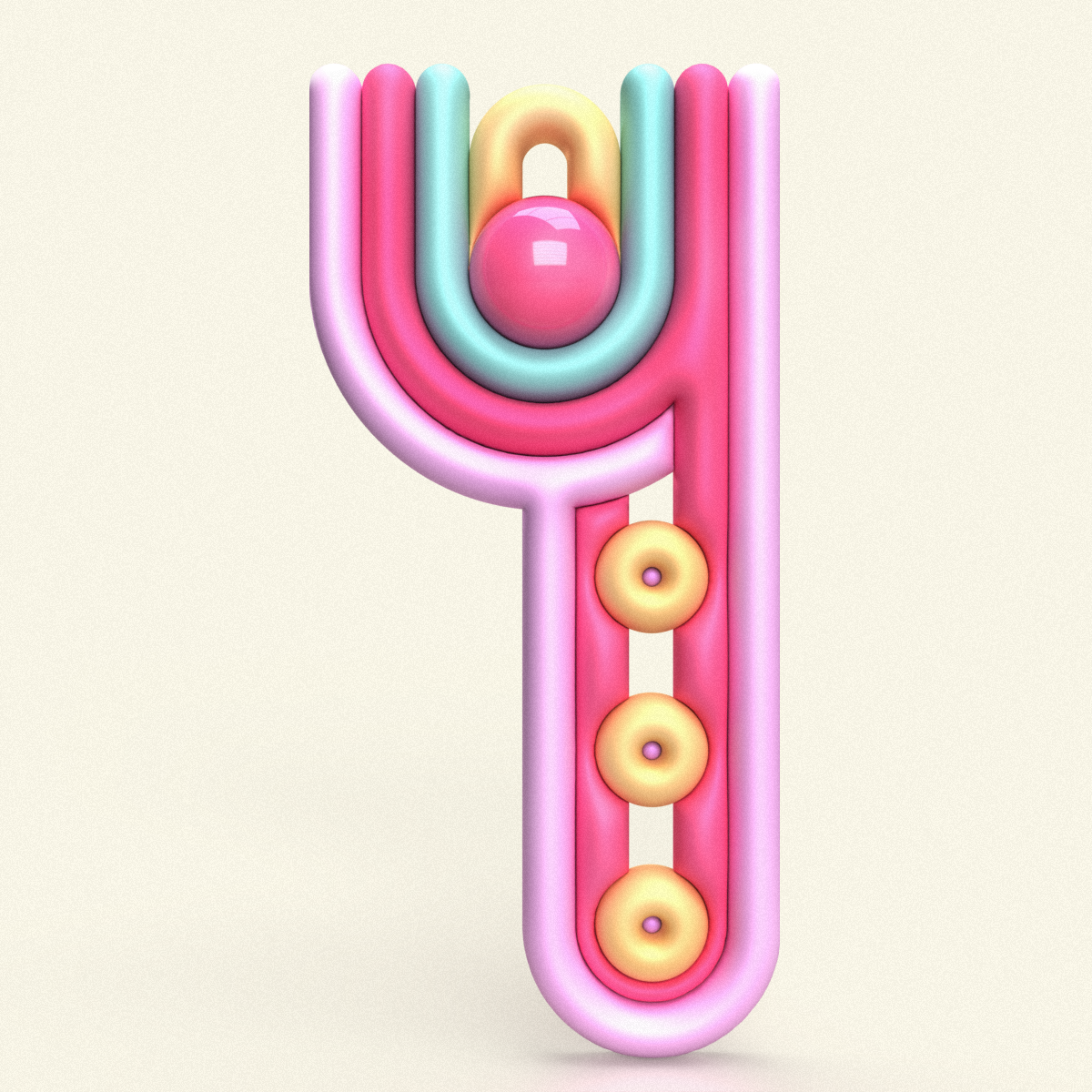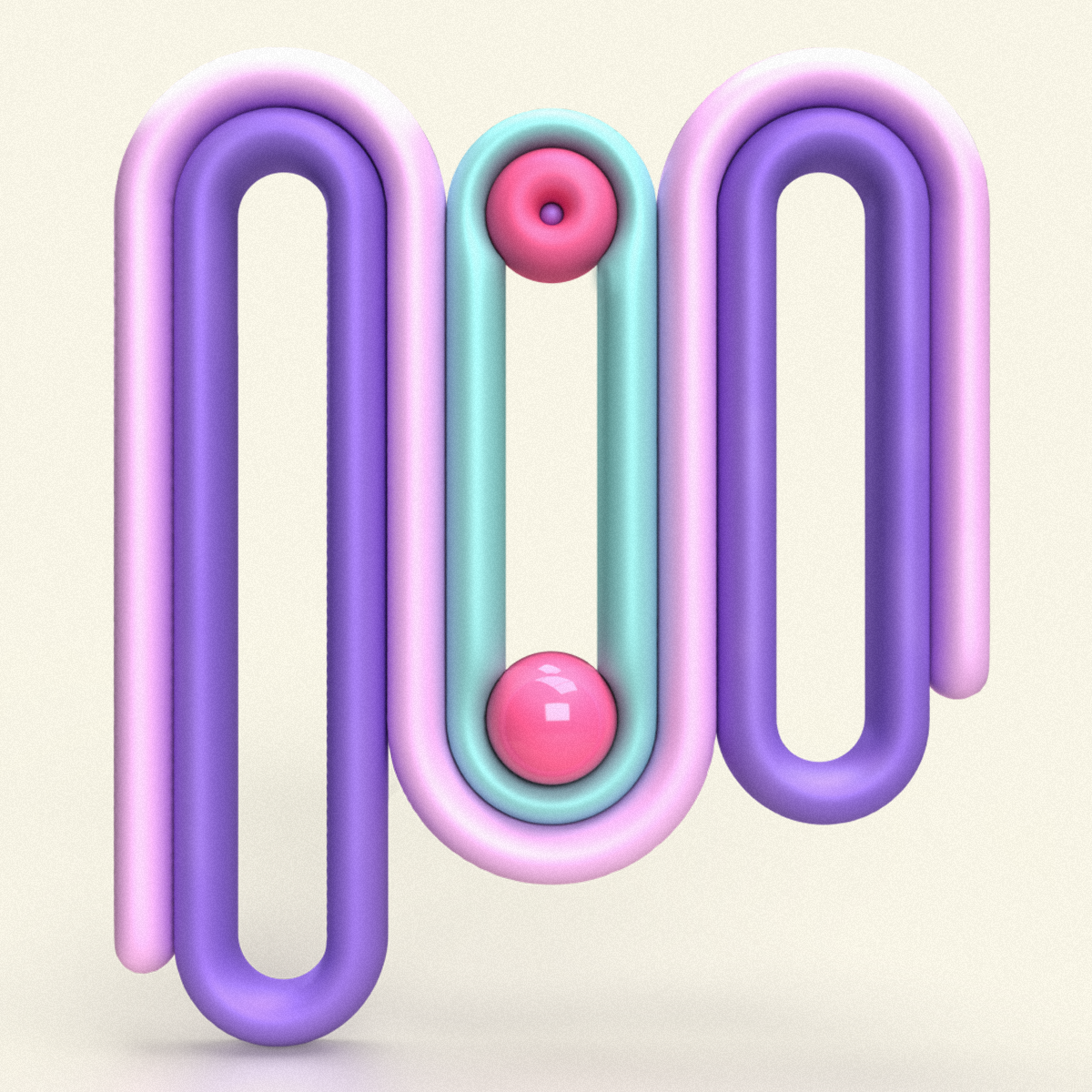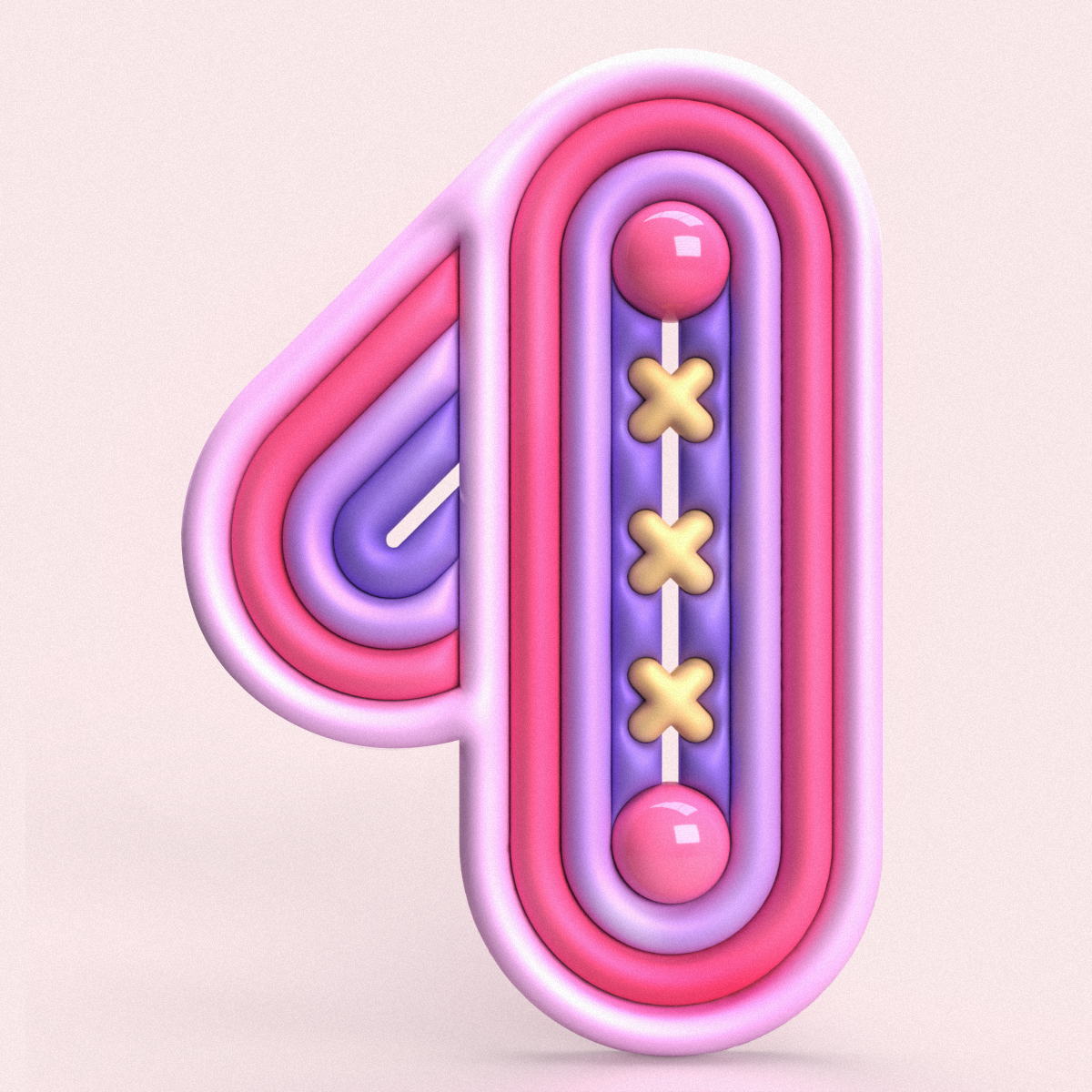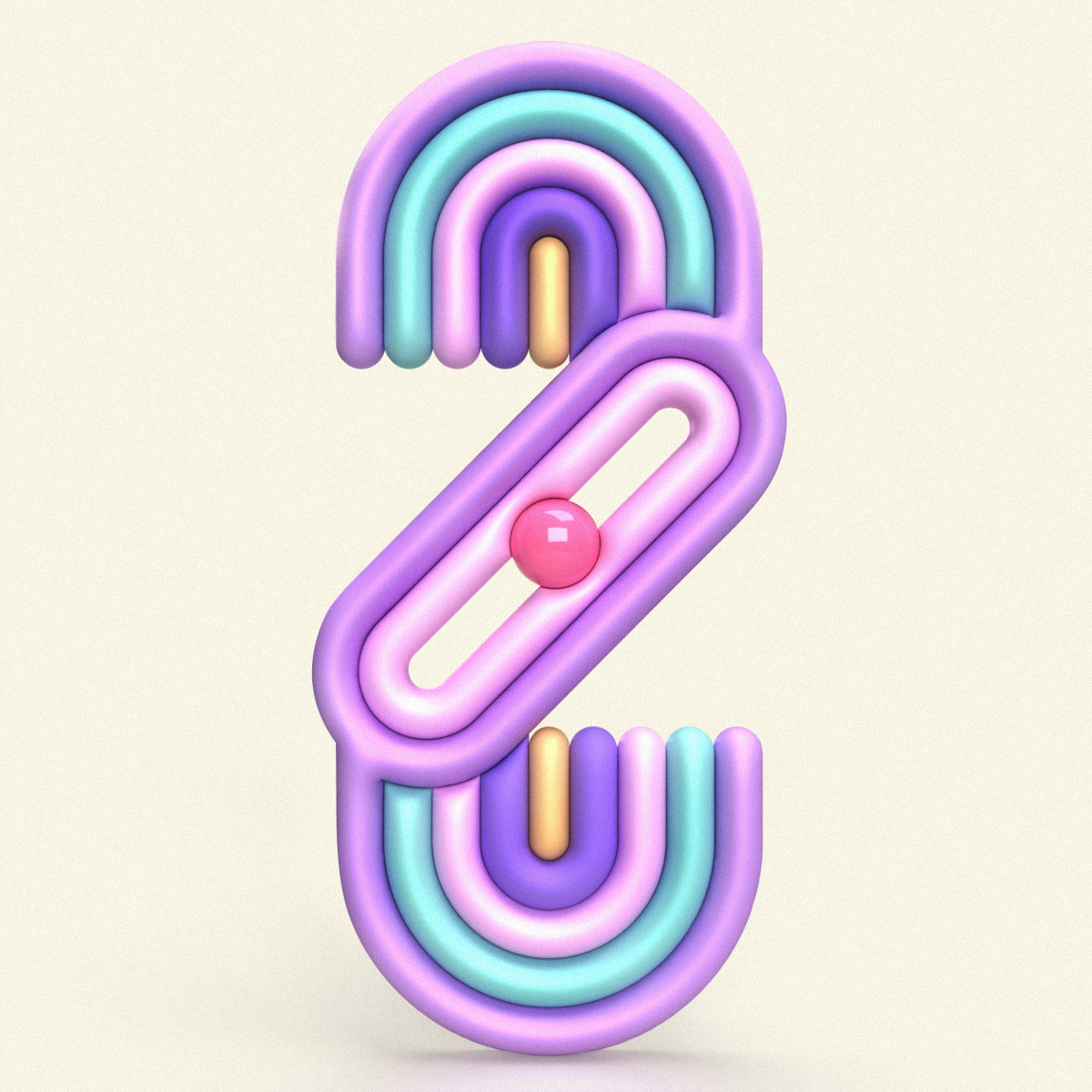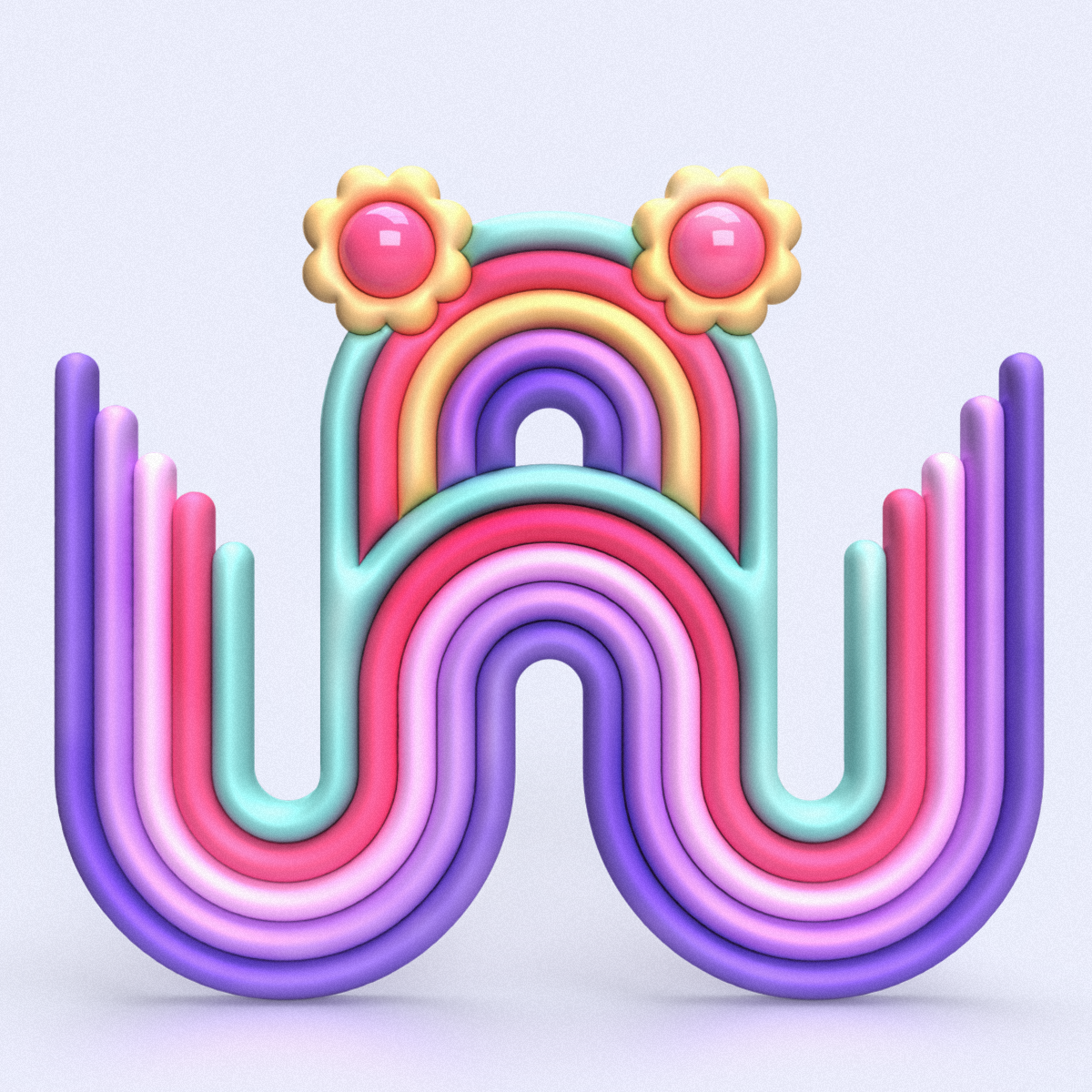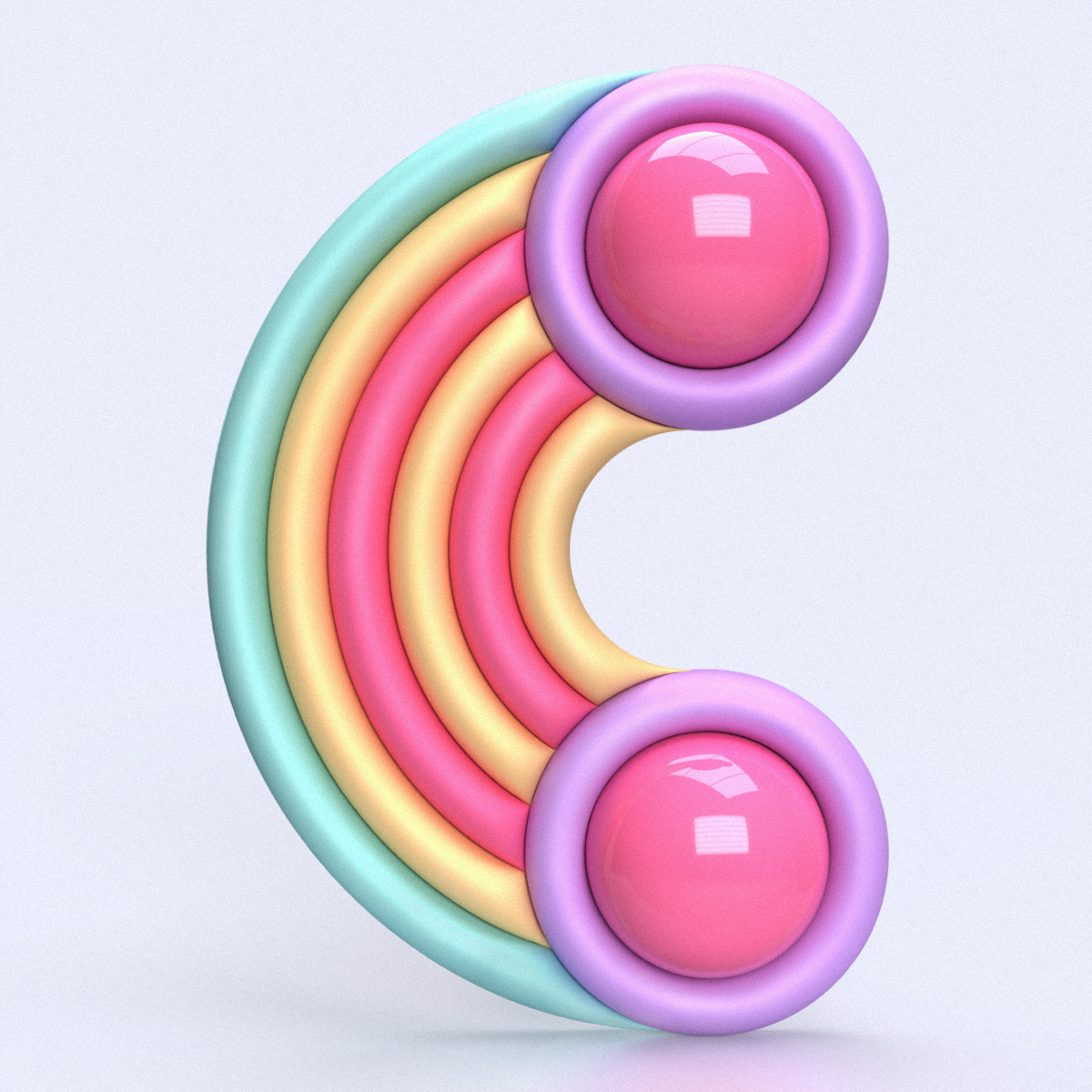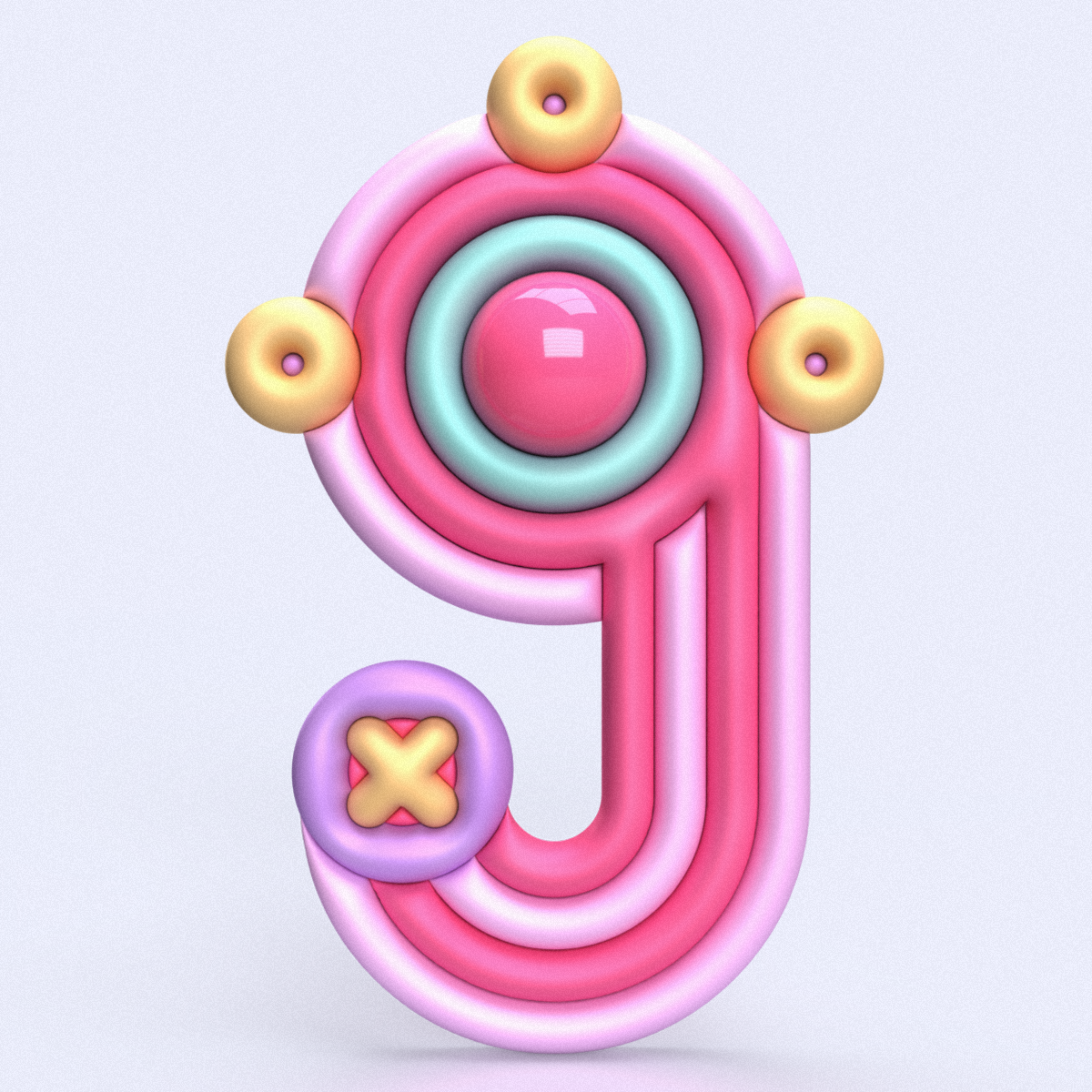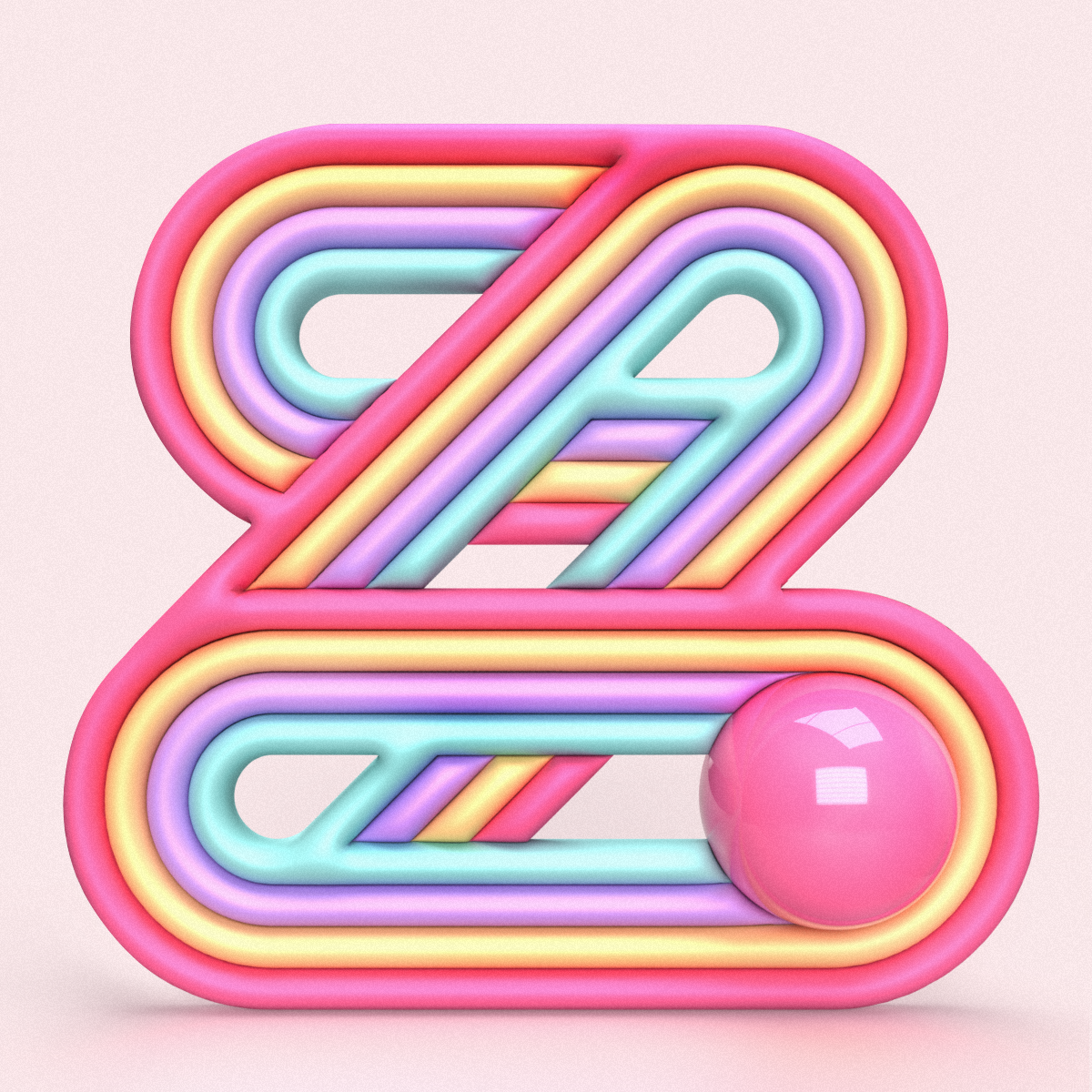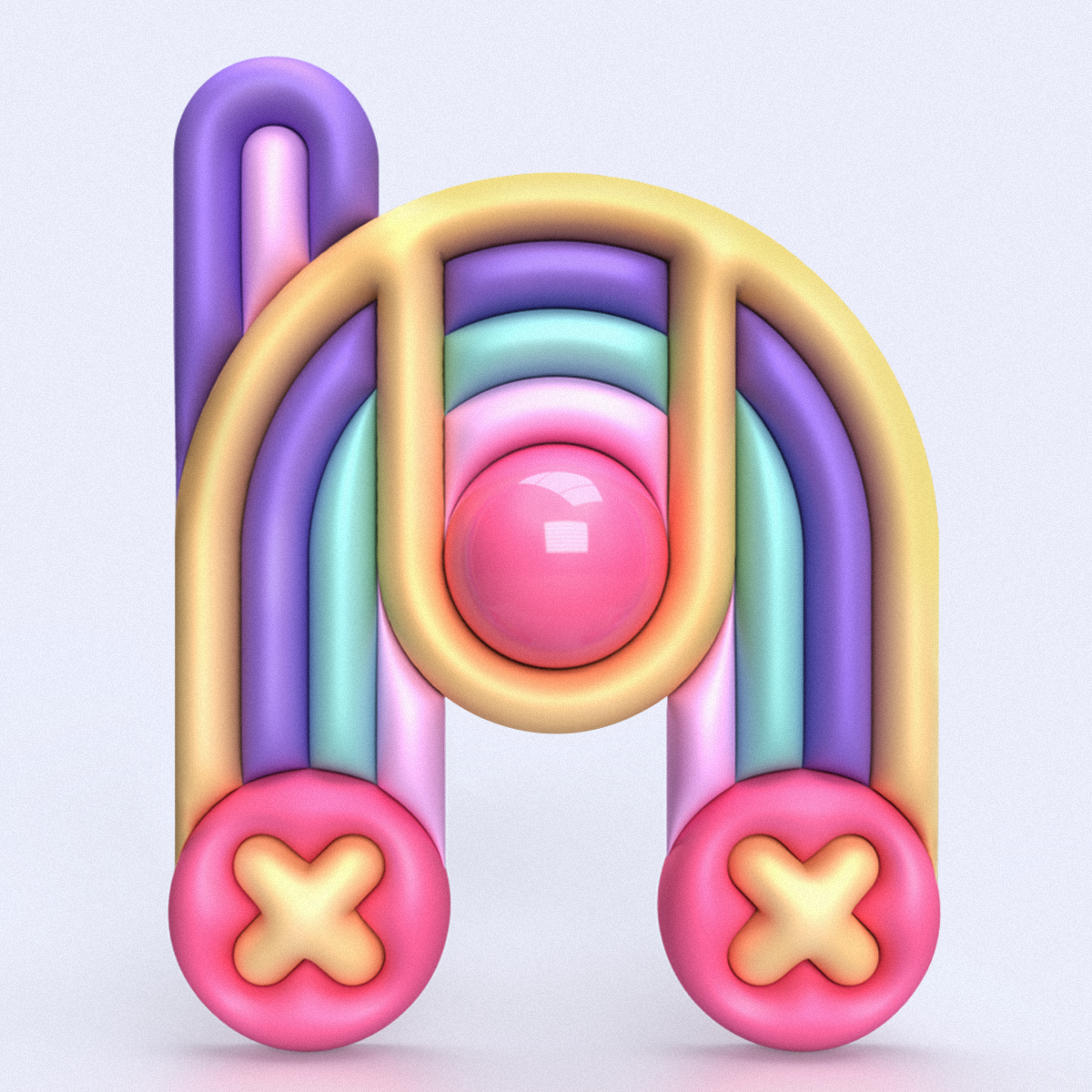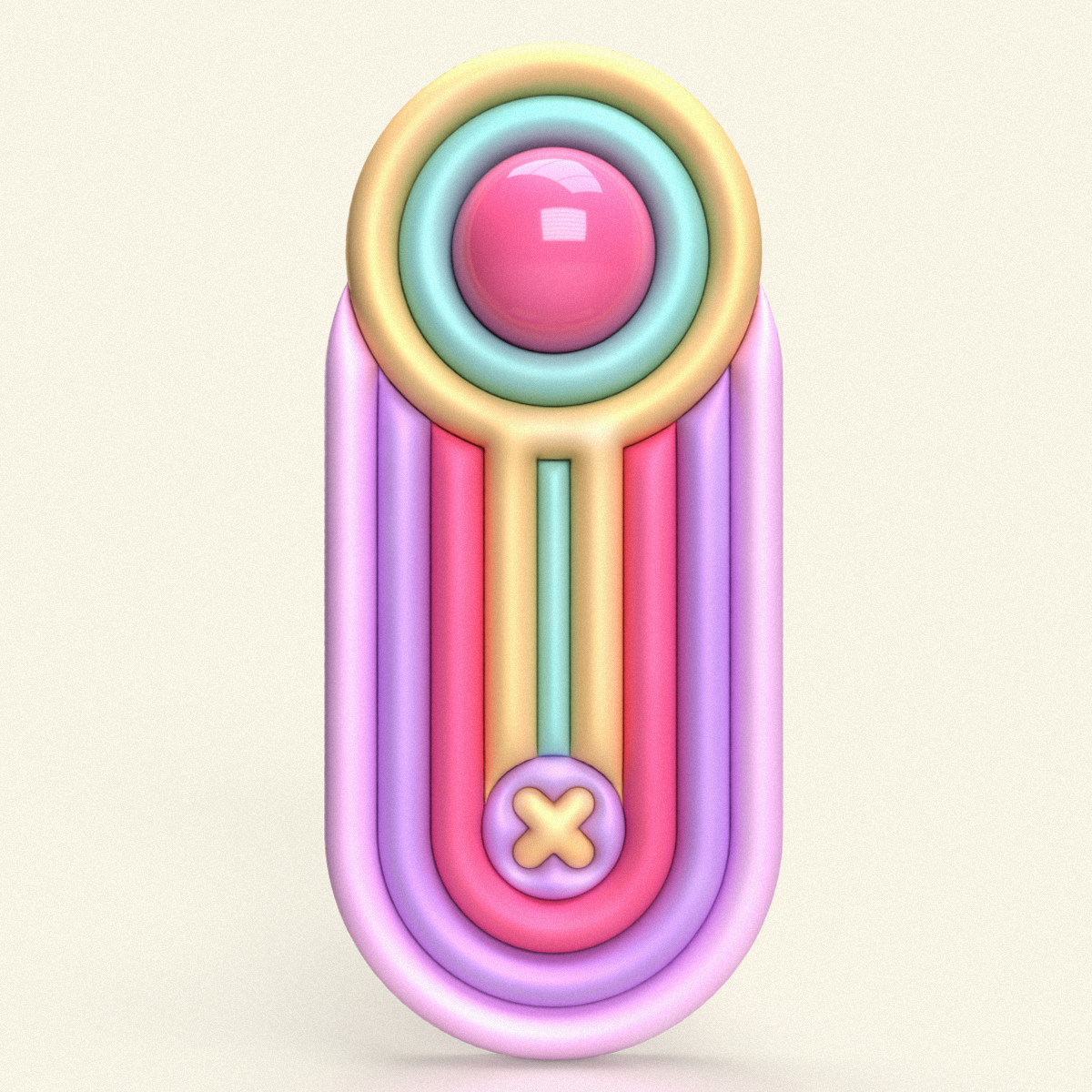
Tercer año consecutivo en 36 Days of Type, una convocatoria abierta a la creatividad donde diseñadores de todo el mundo se apresuran a publicar una letra al día, ejercitando sus estilos creativos más personales y experimentales.
En esta oportunidad decidí trabajar con la unión de dos programas: Adobe Illustrator y Adobe Dimension consiguiendo una serie más cohesiva en su conjunto y desarrollando una tipografía en 3D divertida y casual.